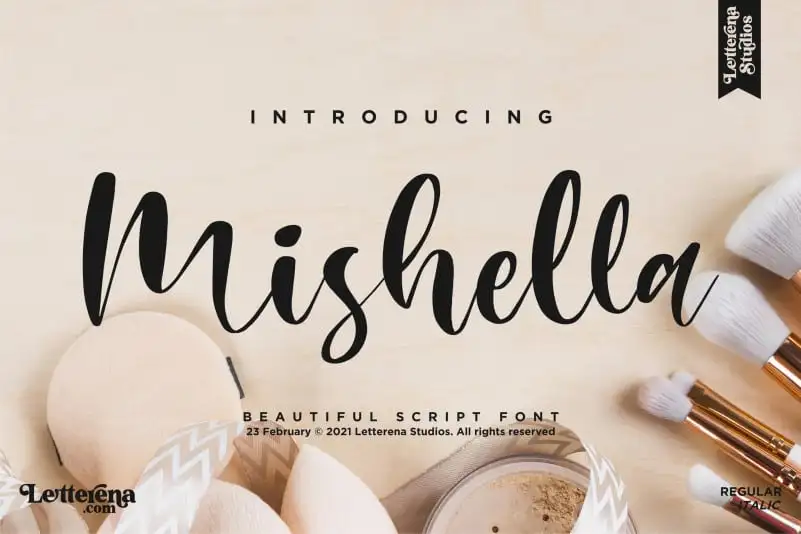
Mishella Script Font – Download Grátis
A Mishella Script Font é uma delicada escritura romântica desenvolvida pelo Designer Letterenastudios. Esse elegante tipo de letra atinge uma variedade de projetos, desde logotipos e projeto de marca até designs para produtos, embalagens e objetos cotidianos. É perfeito para aqueles momentos especiais em qual você precisa daquela pitada única e sofisticada de um bom texto script. Seja na criação de etiquetas, camisetas personalizadas, desenhos de presentes ou capas de livros, a Mishella Script se adaptará perfeitamente. Além disso, ela é o tipo certo para aqueles momentos memoráveis em sua vida, como festivais e eventos especiais. Essa fonte é ideal tanto para designers profissionais quanto para amantes da arte que procuram um toque único e delicado a seus projetos. Composta com perfeição e cuidadosamente desenvolvida, Mishella Script é uma escolha ideal para quem procura mais do que apenas um tipo de letra; ela oferece o equilíbrio perfeito entre ser elegante e suave ao mesmo tempo em que é versátil o suficiente para atender a vários requisitos.